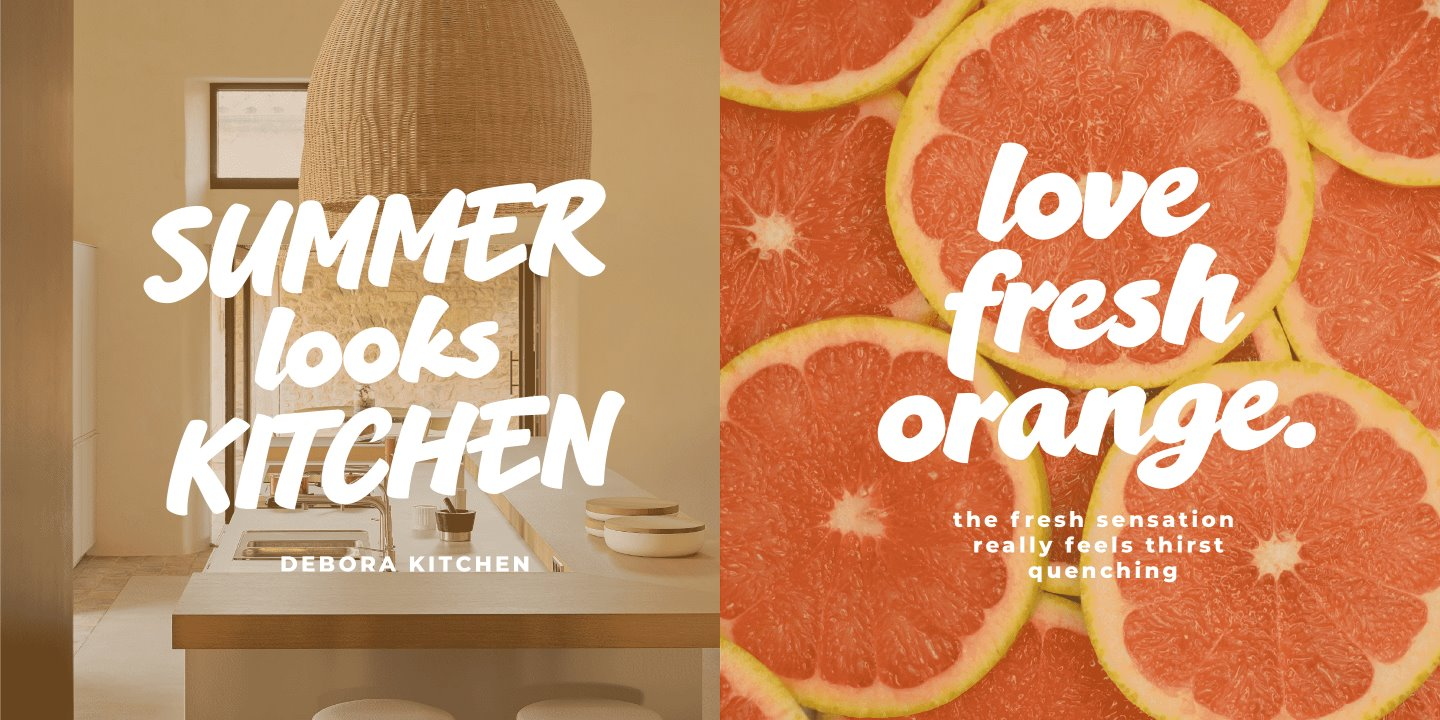
Bacony Script Font
Description de Bacony Script Font
Bacony Script Font est une police de script en gras. Cette police rustique est expressive et composée de gros coups de pinceau et de formes de lettres lourdes. Utilisez-le pour un logo ou un titre comique afin de donner à votre travail un véritable aspect peint à la main. La famille Bacony Script se compose de quatre polices de haute qualité : Regular, Italic et Bold Italic.
La police est construite avec la fonctionnalité avancée OpenType. Il garantit une qualité de premier ordre, contenant des alternatives stylistiques et contextuelles, des ligatures et davantage de fonctionnalités pour vous offrir un contrôle et une personnalisation complets. Il dispose d’un support linguistique étendu, couvrant toutes les langues latines de l’Europe du Nord à l’Afrique du Sud et de l’Amérique à l’Asie du Sud-Est. Il contient tous les caractères et symboles dont vous aurez besoin, y compris la ponctuation et les chiffres.